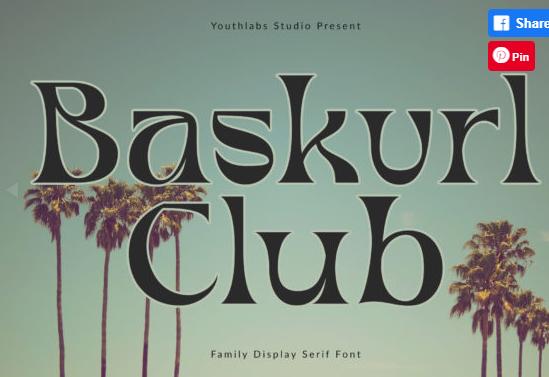
[Creativefabrica] Baskvrl Club Font (youthlabs)
Baskvrl Club - курсивный и жирный шрифт с засечками, идеально подходящий для добавления контрастного акцента в ваши проекты! Уникальный и креативный, этот шрифт способен улучшить внешний вид любой ремесленной идеи!